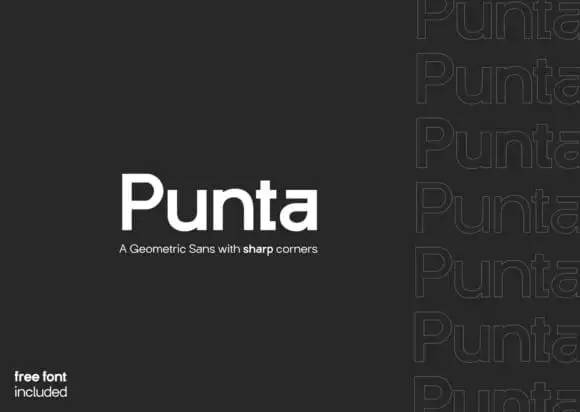
Punta Sans Serif Font – Download Grátis
A Punta Sans Serif é uma fonte sem serif que se destaca pela sua simplicidade elegante e força visual nos textos modernos. Esta fonte ideal para design de mídia, onde você deseja destacar mensagens em headlines atraentes. Com sua estrutura limpa e direta, a Punta cria um texto notável no seu design, tornando-o mais autêntico e interessante. O estilo minimalista da Punta permite que ela se adapte a uma ampla variedade de projetos desde capas de revistas e flyers até embalagens e selos, mantendo sempre o equilíbrio entre modernidade e elegância. Esta fonte pode realmente se tornar sua escolha preferida para um grande número de trabalhos gráficos, independentemente do propósito. A Punta Sans Serif é a escolha perfeita para designers buscando uma combinação única de simplicidade e modernidade em suas criações visuais.